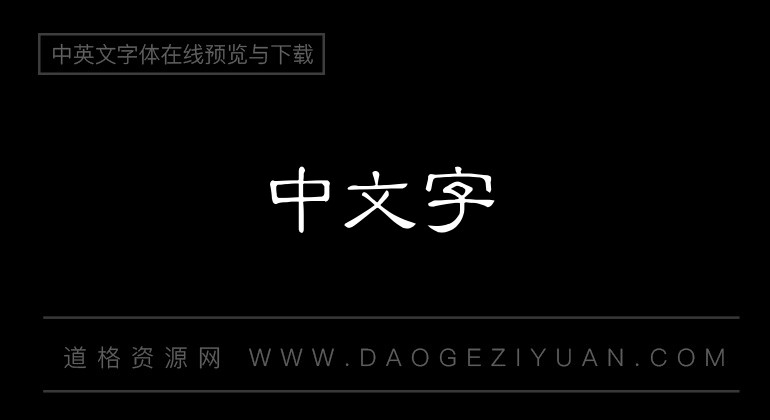
金梅简体细隶国际码字体是一款专为中文网页设计者所精心设计的字体,其字形细腻,笔画简洁,符号精确,极具网页设计风格,是最佳的中文网页字体之一。金梅简体细隶国际码字体采用Unicode编码,可以实现全球范围内的字符编码,以及国际标准的字符编码,可以支持多语言显示,支持多种字符集,可以支持中文、英文、日文、韩文等多种语言的显示,可以满足多种网页设计需求。文件名:JinMeiJianTiXiLiGuoJiMa-1.ttf
金梅简体细隶国际码是一款非常不错的手写艺术字体,具有很好的视觉感,适合于文化类的宣传设计、商业类品牌的广告和产品包装设计以及个性化文字排版等较多场景。